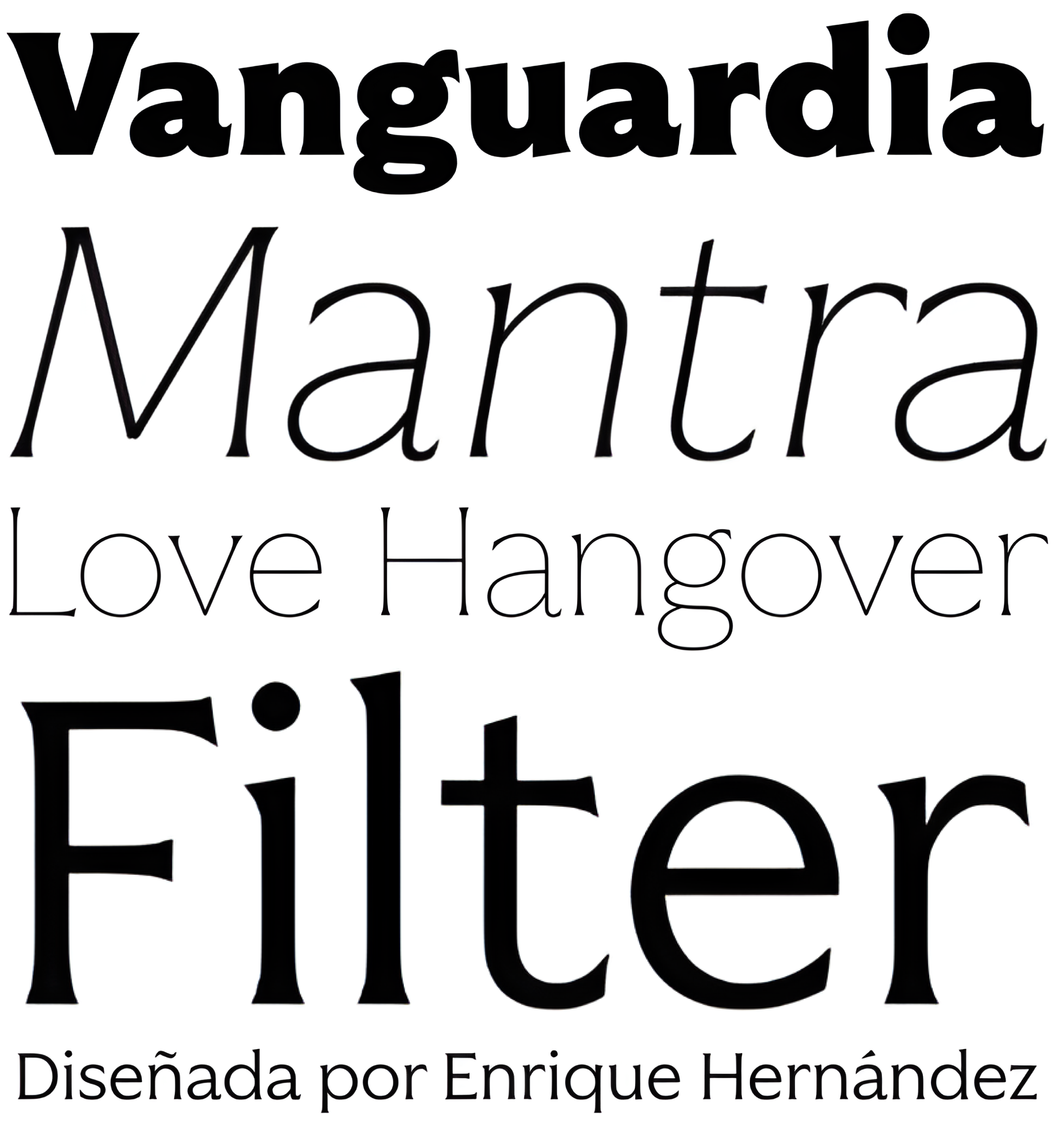
| Descripción | Vanguardia es una expresiva y moderna familia de fuentes con gracias monolineales, que gracias a su bajo contraste se diferencia de las fuentes con gracias tradicionales. Sus terminales llamativamente exagerados, como en las letras a, e, c, y C, S, G y E, etc. Junto con sus cortes diagonales, le confieren un carácter muy singular. Es ideal para logotipos, marcas, envases, títulos de gran impacto, etiquetas, envases de licores y bebidas, así como para su uso en web, cine y televisión. Vanguardia viene con 8 pesos, de fino a negro, y cursivas a juego, lo que da un total de 16 fuentes. Cada estilo de fuente es compatible con más de 200 lenguas latinas. Vanguardia también incluye un juego básico de cirílicos. |